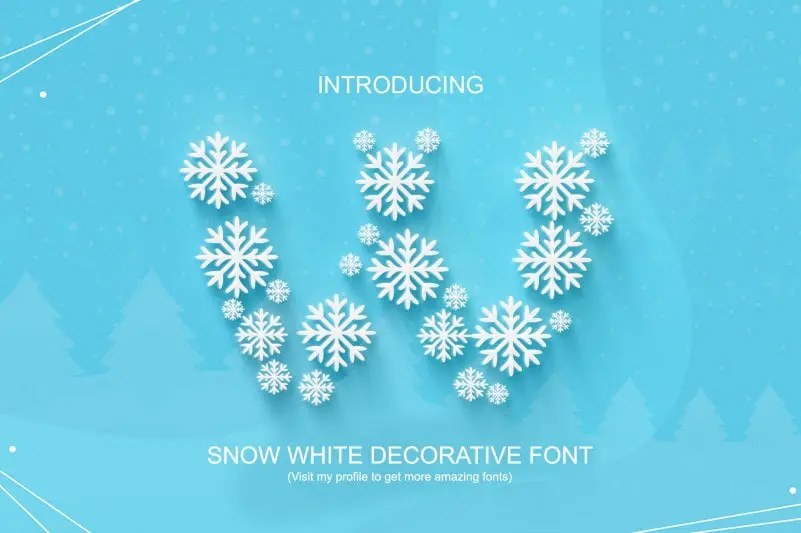
Snow White Font – Download Grátis
Aqui está uma versão em português do Brasil para a descrição do download da font ‘Snow White Font’ na categoria Display Fonts: Esta fonte é um show à parte, onde cada letra é composta de cristais de neve delicados e icônicos. Perfeito para aqueles momentos criativos onde você quer criar um design divertido e autêntico. Seja para nomes de lojas, flyers, ou até mesmo em sua próxima publicação no Instagram, essa fonte dará um toque único e atraente ao seu trabalho. Afonte ‘Snow White Font’ é perfeita para quem busca uma sensação de aventura e autenticidade em seus projetos digitais. Com cristais de neve como base, ela promete trazer um visual elegante e divertido aos seus designs sem perder a qualidade ou a personalização que você espera. Seja para ilustrar uma marca ou decorar sua página de blog, essa fonte é certamente o item ideal para estilos de design modernos e criativos.